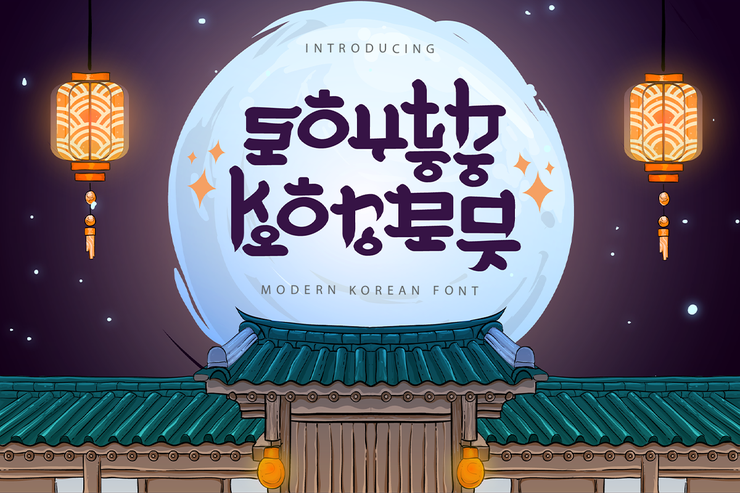
Südkorea Stilvolle koreanisch inspirierte moderne dekorative englische Schrift
Südkorea ist eine einzigartige dekorative englische Schriftart mit kulturellem Thema, die modernes Design mit ästhetischen Elementen im koreanischen Stil verbindet. Sie zeichnet sich durch klare, ausgewogene Striche, weiche Kurven und unverwechselbare stilisierte Details aus und präsentiert ein trendiges, sanftes und exotisches visuelles Temperament. Diese vielseitige Schrift eignet sich perfekt für Reiseposter, Markenlogos im koreanischen Stil, Café & Eacute; Beschilderung, kulturelle Verpackung, Webbanner und Social-Media-Grafikdesign in Bezug auf koreanische Kultur, Mode und Tourismus. Komplett mit Groß- und Kleinbuchstaben ist sie hochgradig skalierbar und lässt sich leicht an Farben, Größen und Layouts anpassen, ohne ihre regionalen Stilmerkmale zu verlieren. Geeignet für Grafikdesigner, Kulturstudios und kommerzielle Markenprojekte, um auffällige visuelle works.Free für die kommerzielle Nutzung zu schaffen / Kein Copyright 1